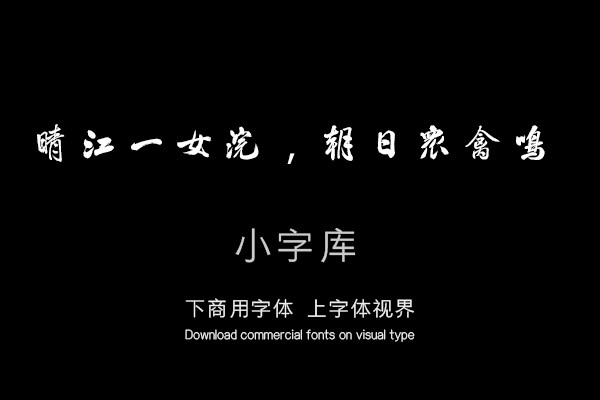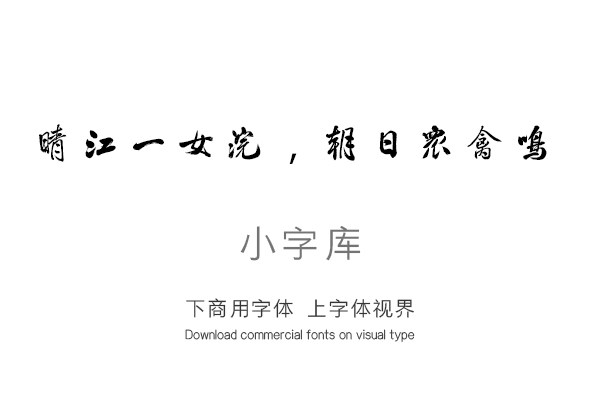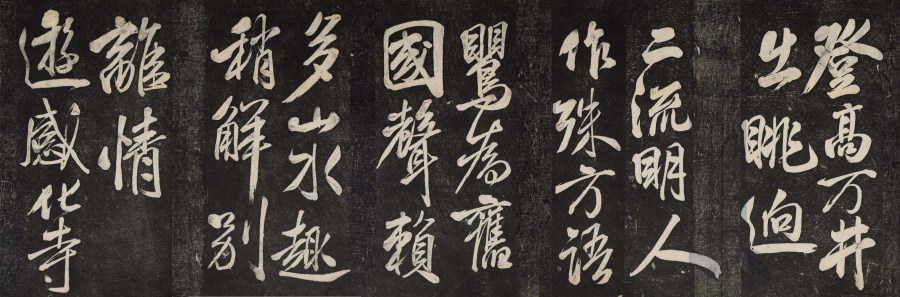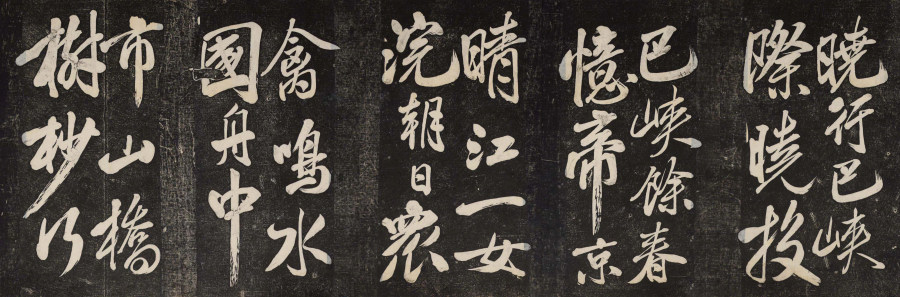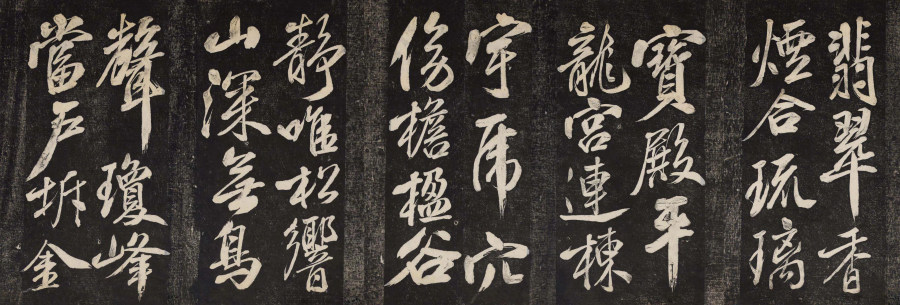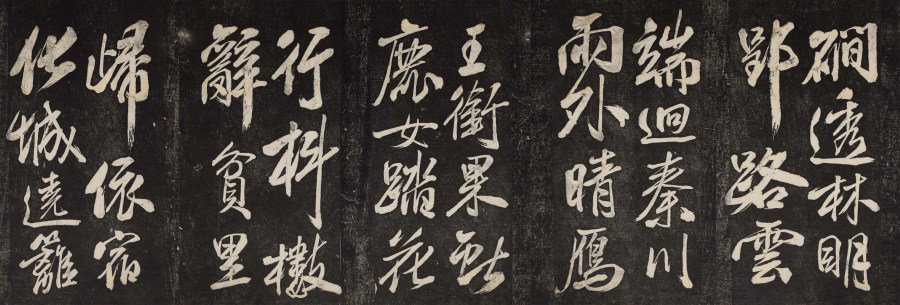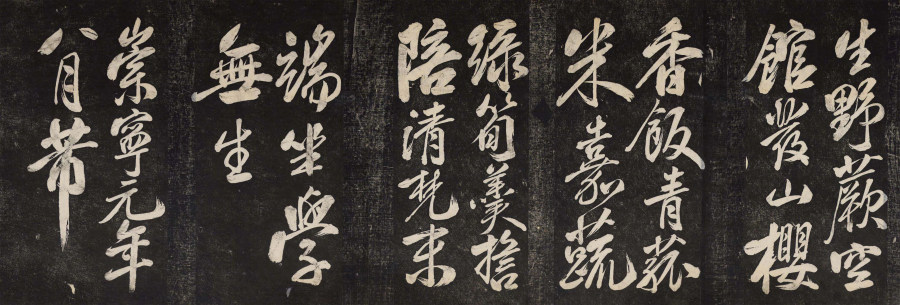
汉标米芾晓行巴峡游感化寺
《汉标米芾晓行巴峡游感化寺》是一款根据宋代米芾的大字真迹晓行巴峡游感化寺,经过再次调整制作的小字库,该小字库共收录了该真迹作品中约213个字体。
《晓行巴峡》际晓投巴峡,馀春忆帝京。晴江一女浣,朝日众禽鸣。水国舟中市,山桥树杪行。登高万井出,眺迥二流明。人作殊方语,莺为旧国声。赖多山水趣,稍解别离情。 《游感化寺》翡翠香烟合,琉璃宝殿平。龙宫连栋宇,虎穴傍檐楹。谷静唯松响,山深无鸟声。琼峰当户拆,金涧透林明。郢路云端迥,秦川雨外晴。雁王衔果献,鹿女踏花行。抖擞辞贫里,归依宿化城。绕篱生野蕨,空馆发山樱。香饭青菰米,嘉蔬绿笋羹。誓陪请梵末,端坐学无生。崇宁元年八月,芾。